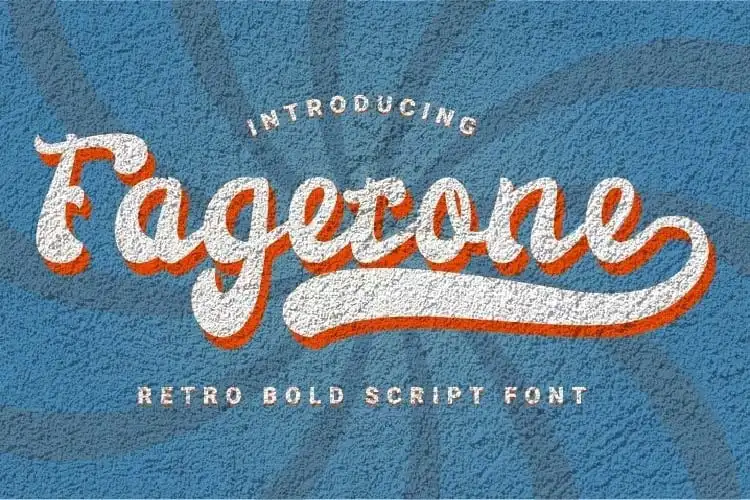
Fagetone Script é uma fonte script vintage que oferece um toque nostálgico perfeito para quem busca um estilo retro/vintage. Inspirada nos anos 60 e 70, essa fonte clássica apresenta versões em negrito e fina, perfeitas para qualquer projeto. Suportando múltiplas línguas e a adição de caracteres especiais, ela é uma escolha ótima para variedades de mídias impressa e digital, como embalagens de alimentos, lojas de acessórios, coleções de roupas, produtos criativos, lojas antigos, esportes, entretenimento e até mesmo em logotipos. Com Fagetone Script, você pode criar designs memoráveis que se destaquem nos mais variados formatos de mídia.